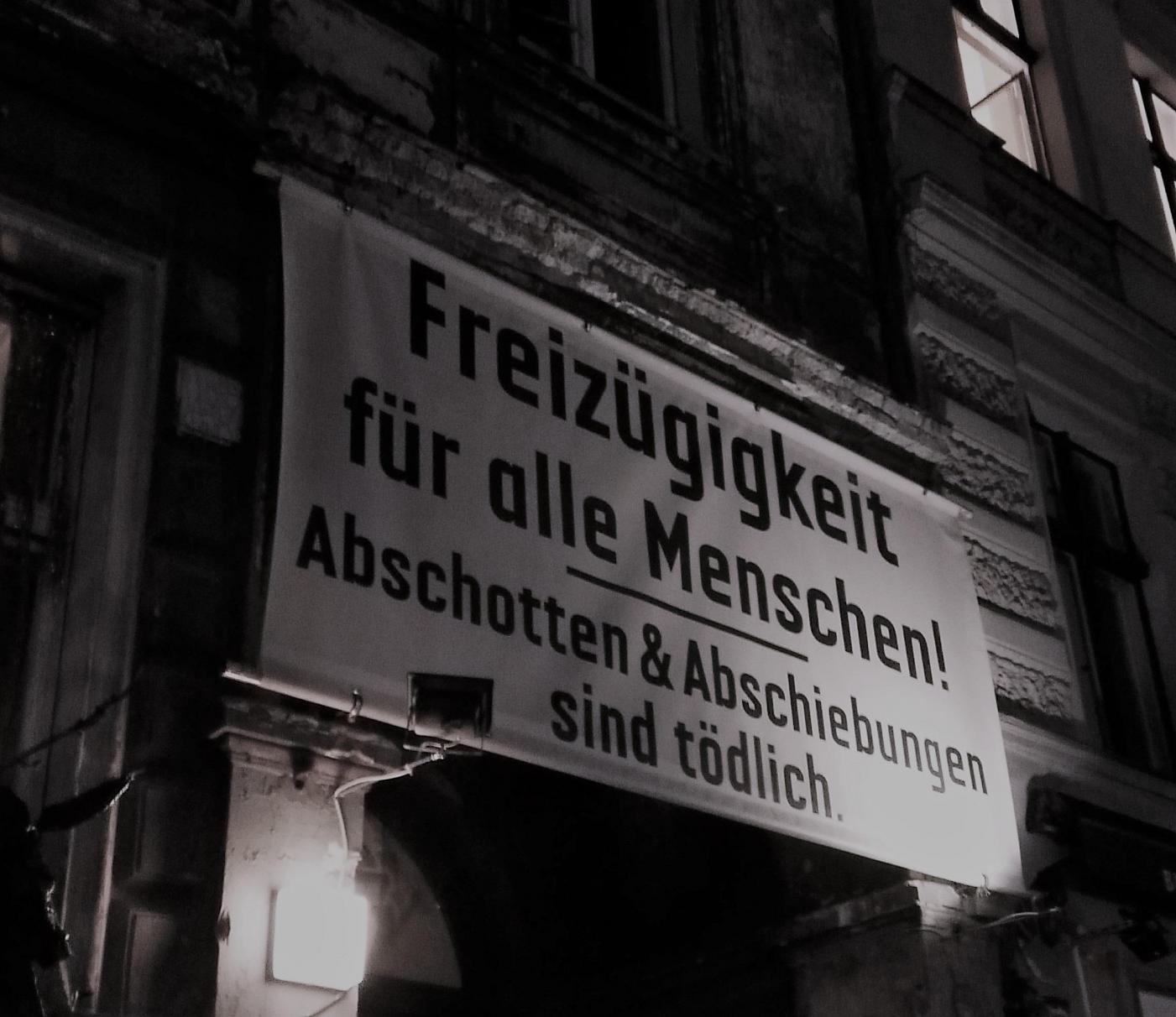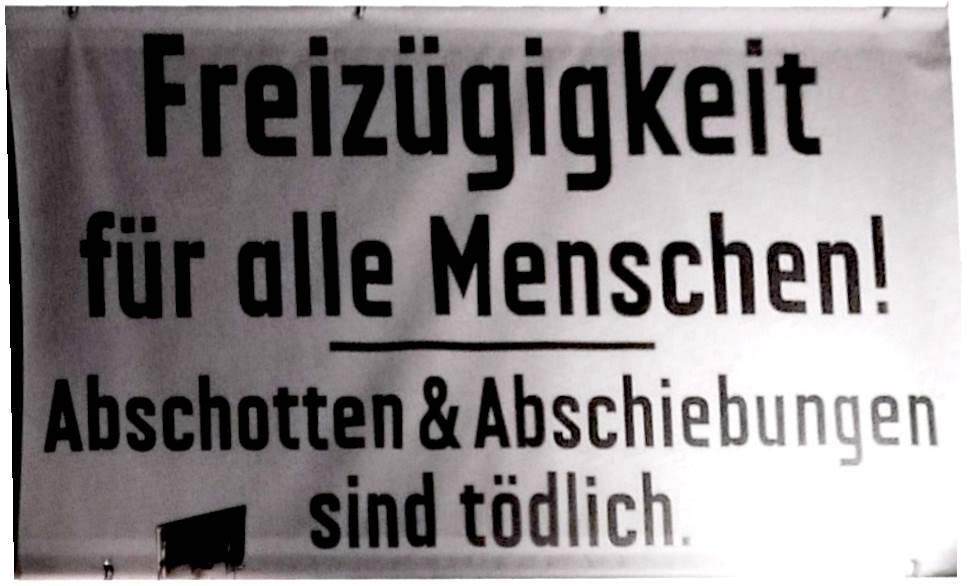
Suche diese alte Schriftart
ich habe heute dieses Transparent gesehen und suche nach dieser meiner Einschätzung nach etwa um 1900 und auch später genutzten und auf älteren Flugblättern oft anzutreffenden, serifenlosen Schrift (s. Anhang). WhatTheFont konnte mir - wohl wegen der Ausrichtung meines Bildes - nicht weiterhelfen.